『TPスカイ開発ストーリー』第6回「TPスカイの構想と展望」(最終回)
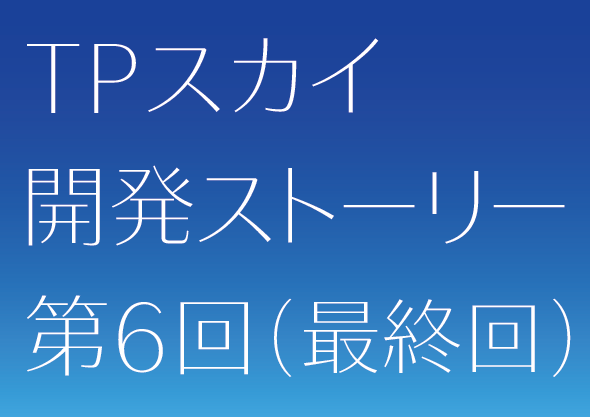
■まえがき
2ヶ月半にわたって書き継いできた「TPスカイ開発ストーリー」の最終回です。目線をすこし上にあげて、TPスカイの構想と展望について書いてみたいと思います。
はじめにTPスカイの開発方針を要約しておきます。
1. 澄明でクリアなデザイン
2. 画面表示に適した簡潔なアウトライン
3. 様々な状況に対応できる幅広いファミリー
そして、TPスカイの開発でチャレンジした課題は次の3点です。
・審美性と機能性をどのように両立するか
・サンセリフ体の品質をどこまで上げられるか
・抑揚サンセリフのカテゴリーを活性化する
■審美性と機能性をどうやって一体化するか
冒頭で要約した開発方針の1「澄明でクリアなデザイン」は審美性にあたり、2と3が機能性に関する方針になります。「澄明・簡潔」というデザインの方向性は、描画表現と機能的な効果を一体にしたことで、無理なく審美性と機能性の両立を果たしました。
■サンセリフ体の品質をどこまで上げられるか
なぜサンセリフ体の品質を上げる必要があるかといえば、サンセリフ体が丸裸の文字だからです。装飾がないサンセリフ系のフォントは、書体の骨格属性がむき出しになります。裏返して言えば、骨格とウエイトを整えることで簡素な美しさを直接に表現できる書体でもあります。サンセリフ体の品質を上げるのに必要な作業は、次の2点に集約できます。文字の太さおよび黒みを視覚的に揃えること。もうひとつは、カウンターをバランスよく按分することです。もちろん重心などの属性も大事ですが、ウエイトの調整とカウンターの按分に重点を置けば、確実に書体の品質を上げることができます。
品質向上という点では、ウエイトとコントラストの2軸をあつかうTPスカイは、ウエイトのみの調整に比べ、安定性を確保するのがひじょうにむずかしい書体でした。書体品質を向上させるために私たちがとった方策は、独自プログラムを開発することでした。デザイナーの感覚だけで作業を進めるのではなく、プログラムによって感覚のズレや見落としを補ったのです。たとえば、各ウエイトごとにストロークそれぞれの適切な許容値を設定し、その値から外れている文字を弾くなど、計測できる書体属性を洗い出し、理想的な値になっているかどうかをプログラムで調べました。最後はデザイナーの目で入念にチェックして、澄明でクリアなデザインを実現するために、半年以上を費やしてブラッシュアップの作業を繰り返しました。
■抑揚サンセリフのカテゴリーを活性化する
欧米の大手フォントメーカーが公開している売れ筋フォントのランキングをみると、ここ10数年は、サンセリフ体が上位をほぼ独占しています。近年の傾向として興味深いのは、優れた欧文をつくる小規模なフォントメーカーから、ハイコントラスト系のサンセリフフォントが相次いでリリースされている点です。ふだん目にするフォントにサンセリフ体の占める割合が多くなり、それに飽きたらなくなったデザイナーが増え、抑揚をつけたサンセリフ体フォントに注目が集まっているのだとすれば、この流れはしばらく続くでしょう。
■TPスカイの展望
書体の作り手は、フォントという素材を提供する立場で、フォントの使い方は使い手に委ねるのが基本ですが、書体見本帳などでフォントの使用想定例を示すことがあります。下の例は、TPスカイの活用方法に関するタイププロジェクトからの提案です。
情報の階層化は、多くの場合、文字のサイズ差・ウエイト差、スタイル差(明朝 or ゴシックなど)によって図られます。下図のように、TPスカイのコントラスト軸を使い分けることで、これまでのセオリーとは異なる手法で情報の階層化をおこなうことができます。
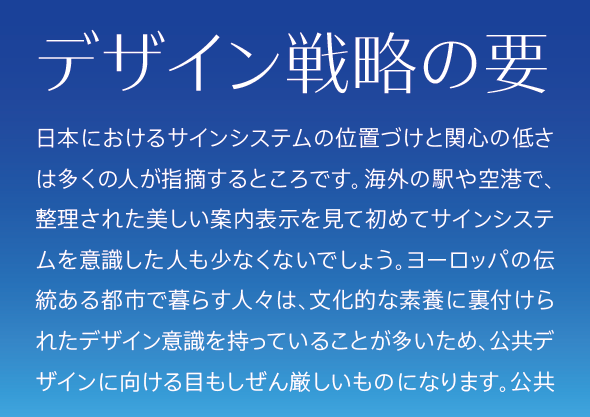
同じウエイトで、コントラストの違いによって印象度に変化をつけた例
見出し:TPスカイ ハイコントラスト L 本文:TPスカイ ローコントラスト L
■最後に
日本語フォントのカテゴリーに、抑揚サンセリフ体が定着するかどうかは分かりません。ひとつ言えることは、スクリーン上のコミュニケーションが、今後もサンセリフ体を中心に進むとすれば、サンセリフ体の品質を上げることが視覚情報のクオリティを底上げする基盤になるということです。現状まだ手薄な日本語サンセリフのファミリーを充実させ、質の高いフォントを増やすことで、日本の UI/UXをより豊かで快適なものにする。タイププロジェクトはこれを重要な課題と考えています。
TPスカイの「澄明な空」というコンセプトは、未来のスクリーンの比喩でもある
「サンセリフ体は、書体の最終段階を表しているわけではない」カール・ゲルストナー
“sans serif does not represent the final stage” Karl Gerstner (Designing Programmes 1964)
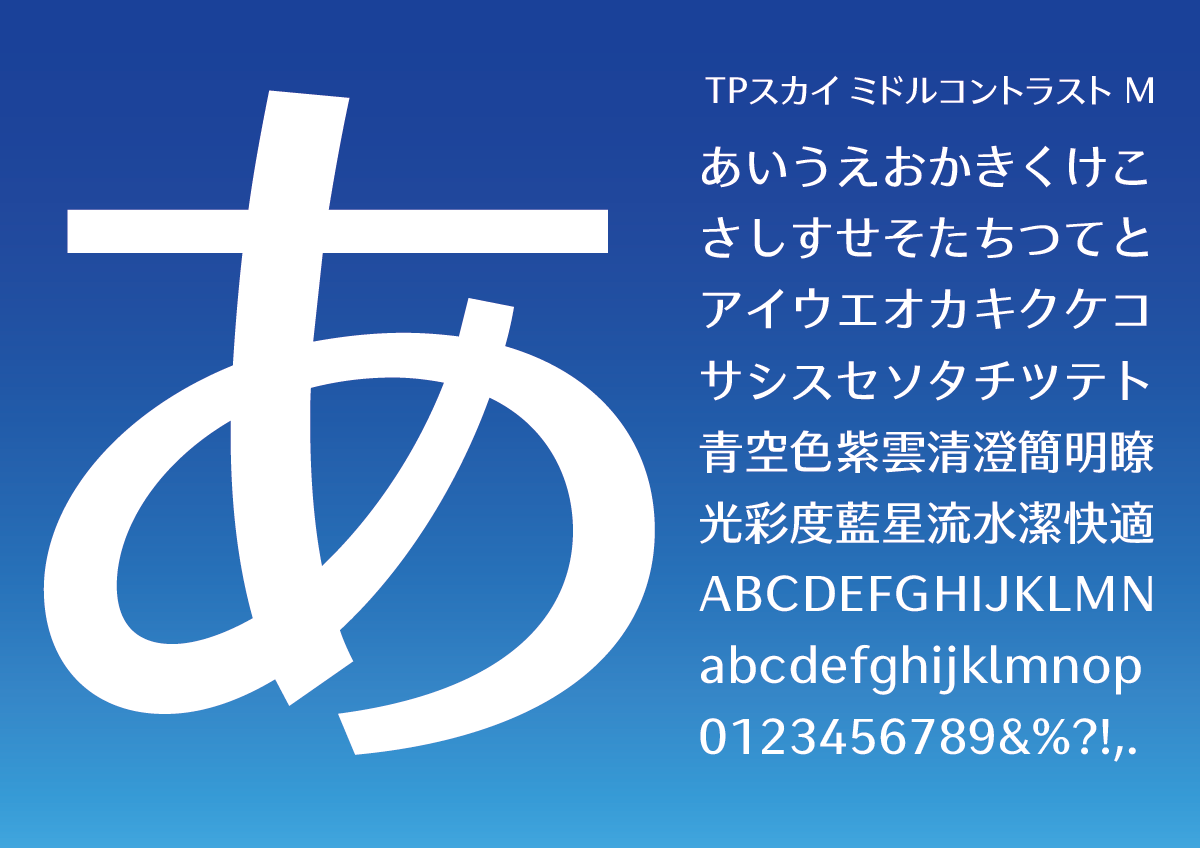
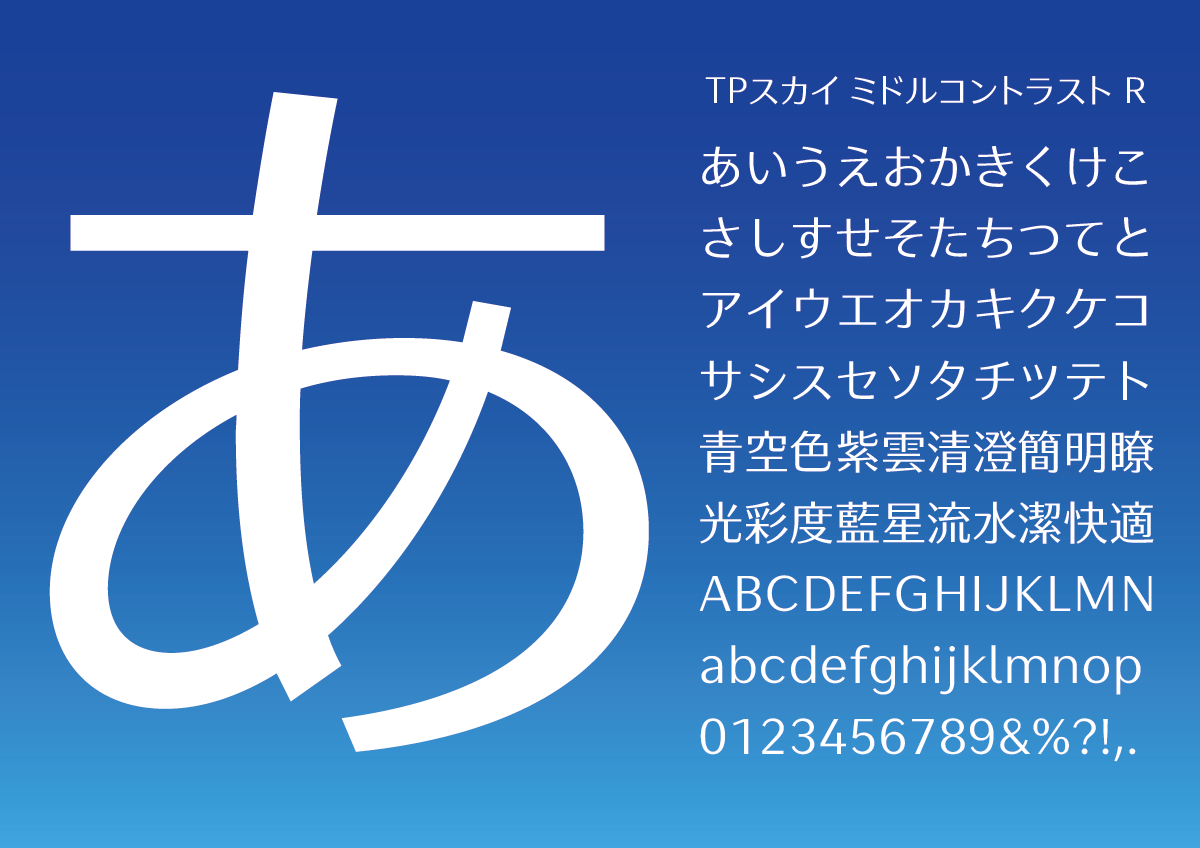
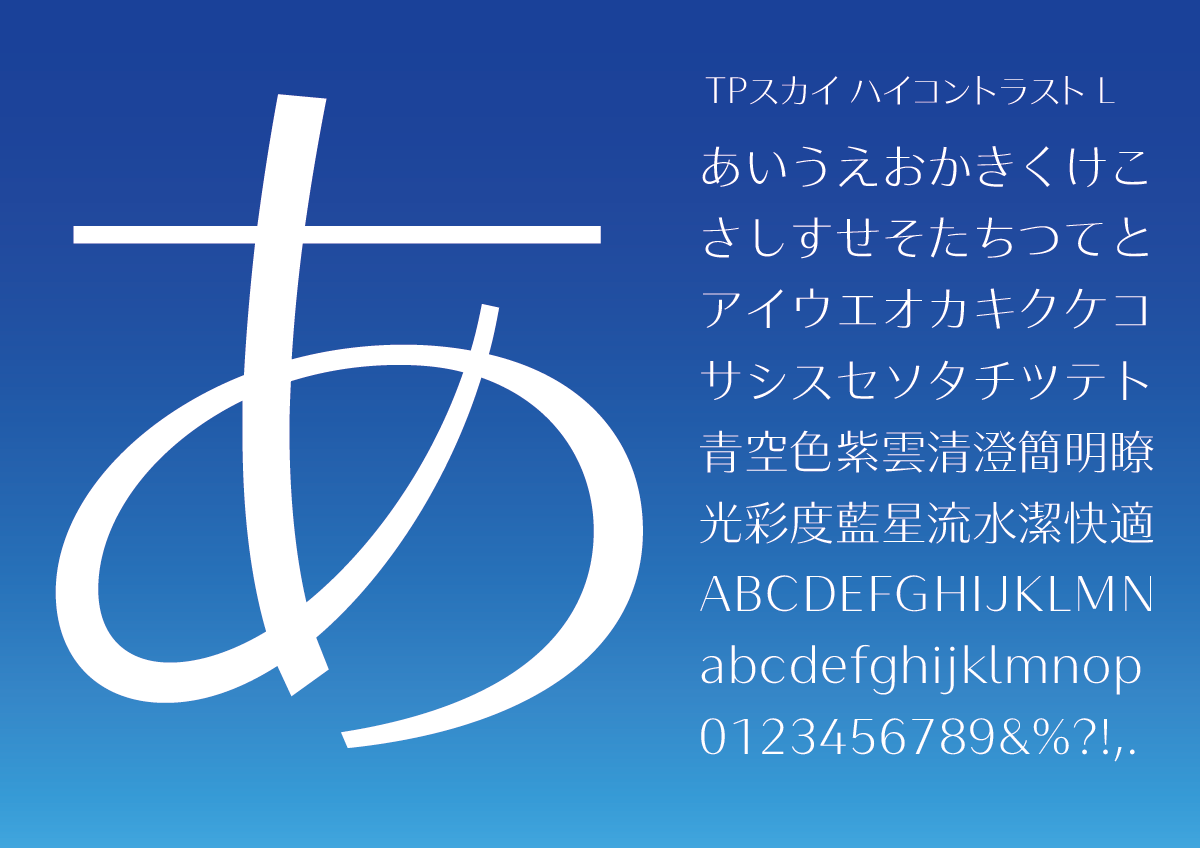
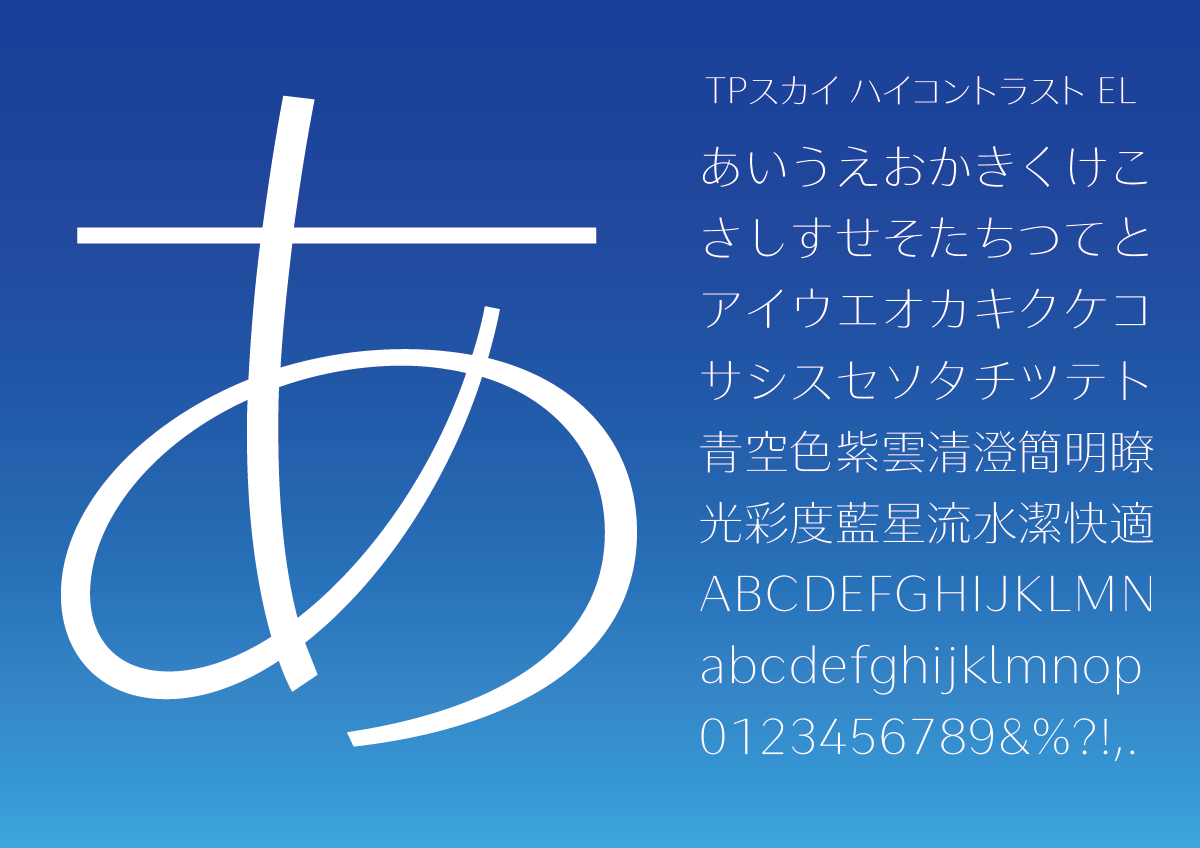
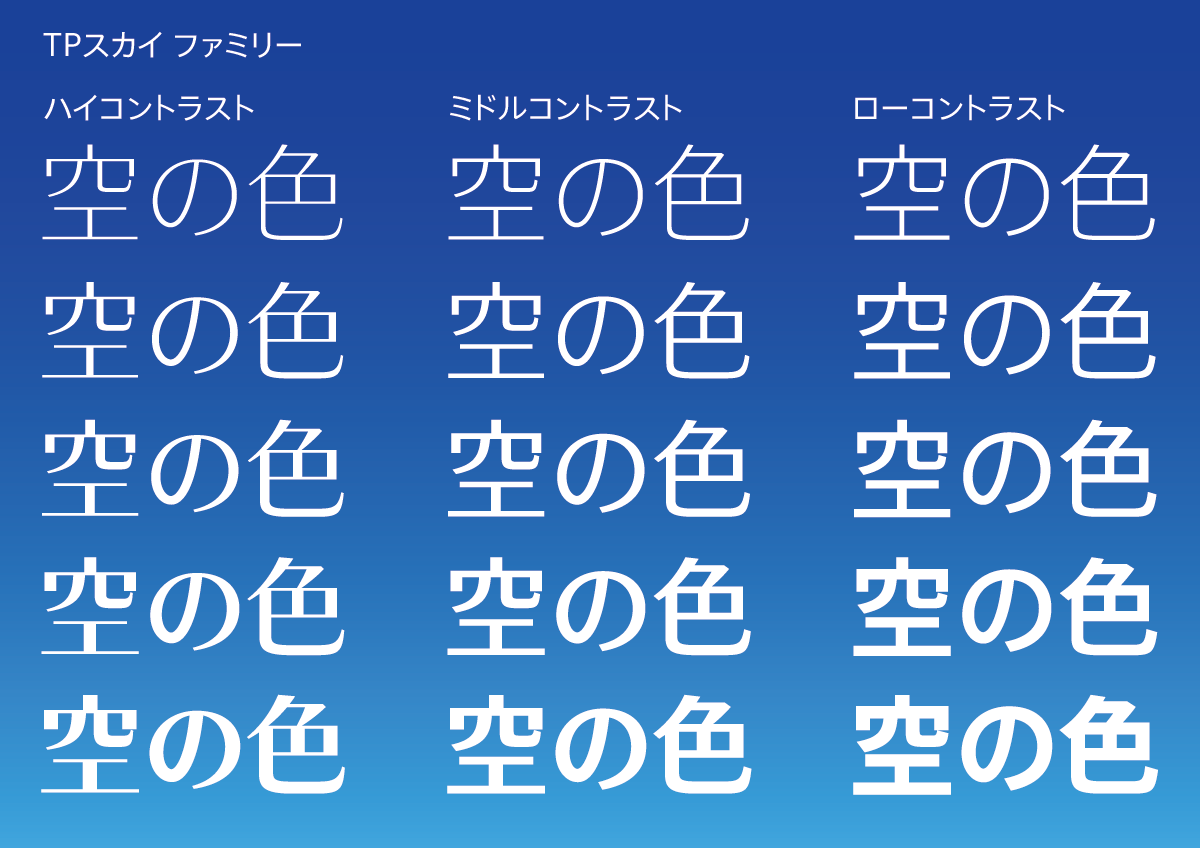
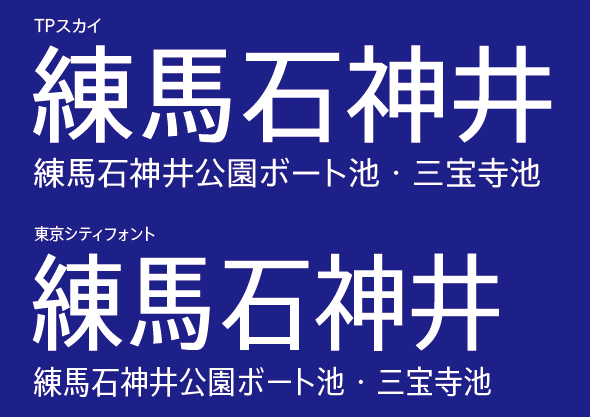
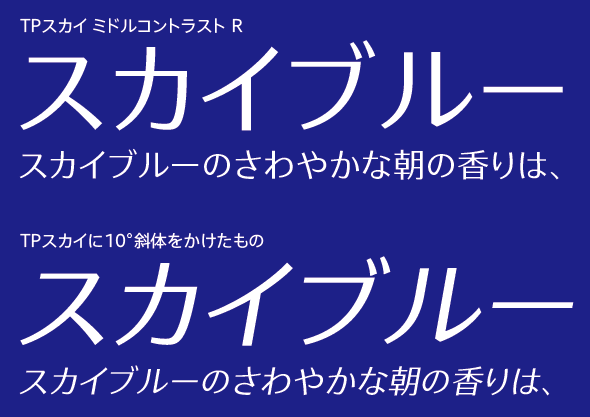
ウエイトの品質を確認するテストシート。確認と修正を繰り返し、徐々に品質を上げていく